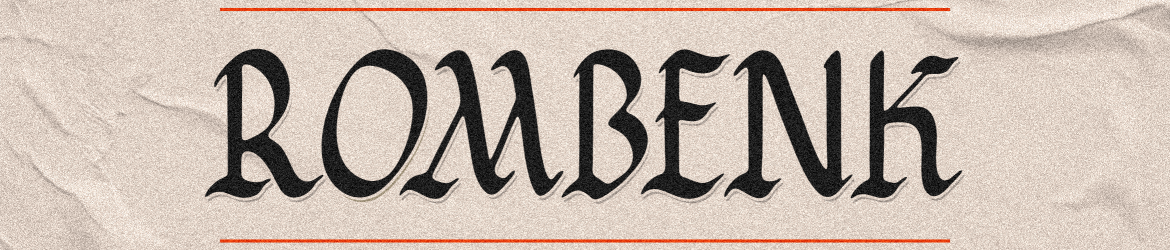
Esta é uma fonte rombênk com detalhes extremamente ricos e presença firme, perfeitamente adaptada para qualquer aplicação visual ou tipográfica. Seja ela um logotipo robusto, um títulos poderoso ou até mesmo o texto interno de uma publicação, este estilo inovador manterá sua identidade única e distinguida sempre presente. O Enigma Lettering Studio trouxe para nós essa fonte inédita que é tanto uma adição como uma experiência. Ideal para quem busca um toque único e atemporal em seus projetos, o Rombenk Font oferece a chance de dar vida à sua ideia com graça e força ao mesmo tempo. Não importa qual seja seu objetivo criativo ou visual – este fonte vai ser definitivamente uma das suas estrelas no seu conjunto de fontes personalizadas.
Designer: Enigma Lettering Studio